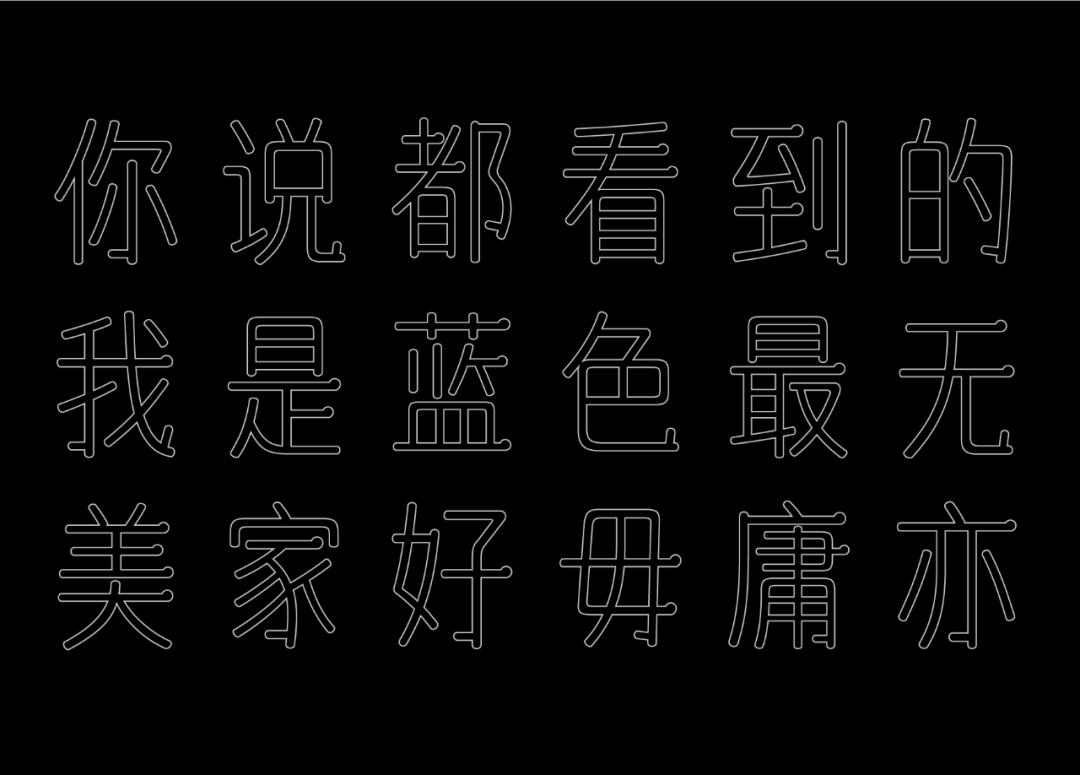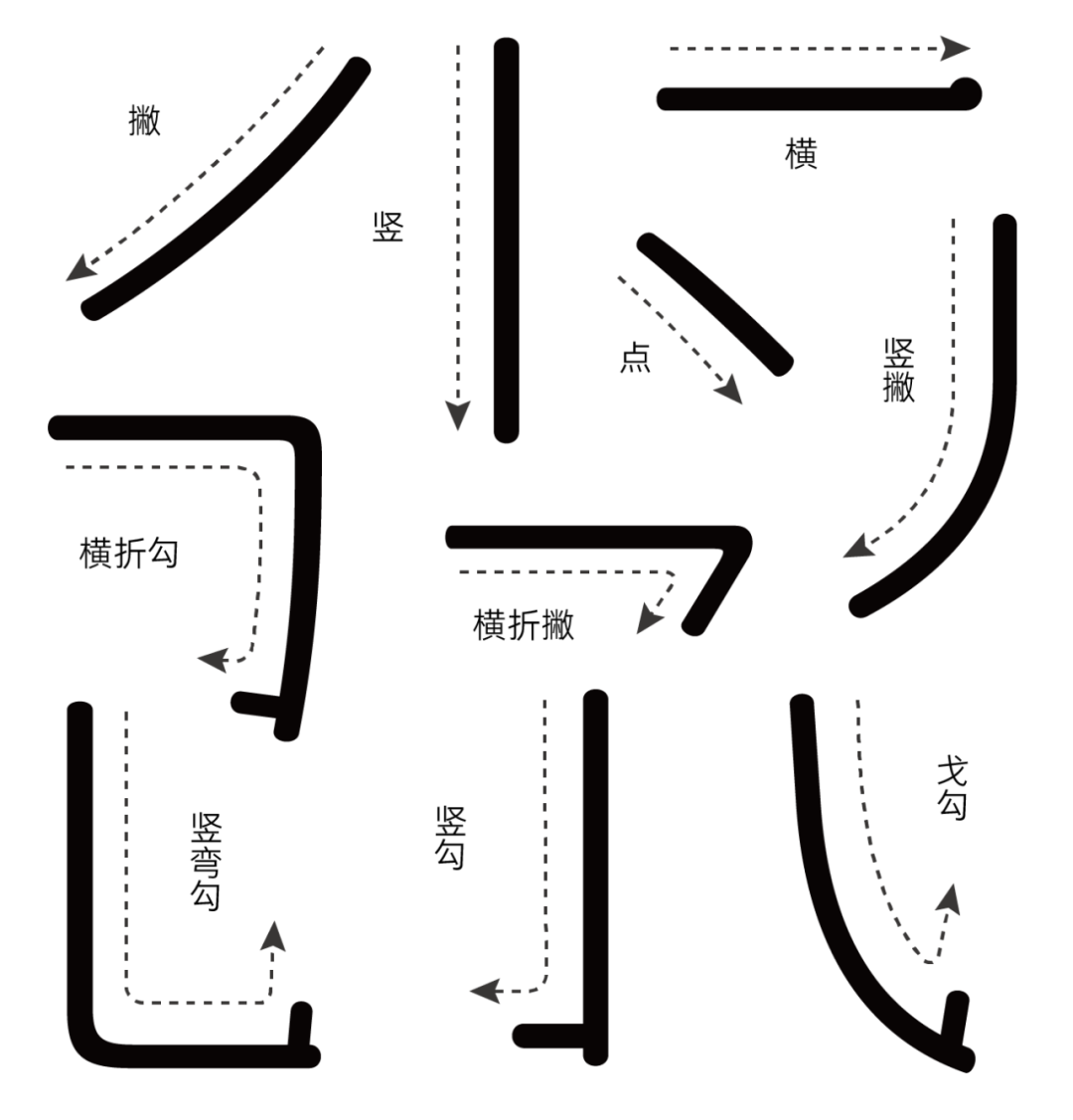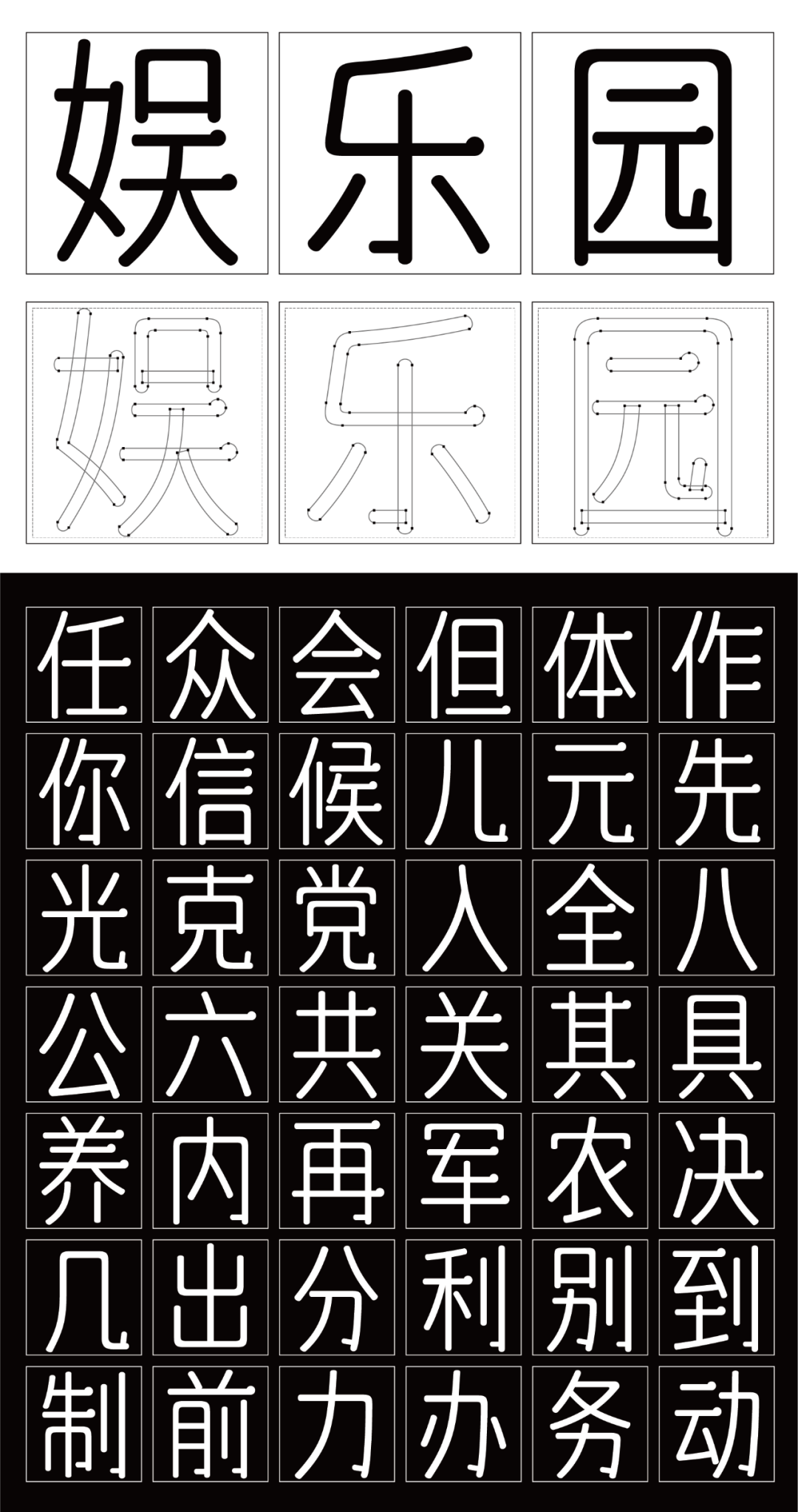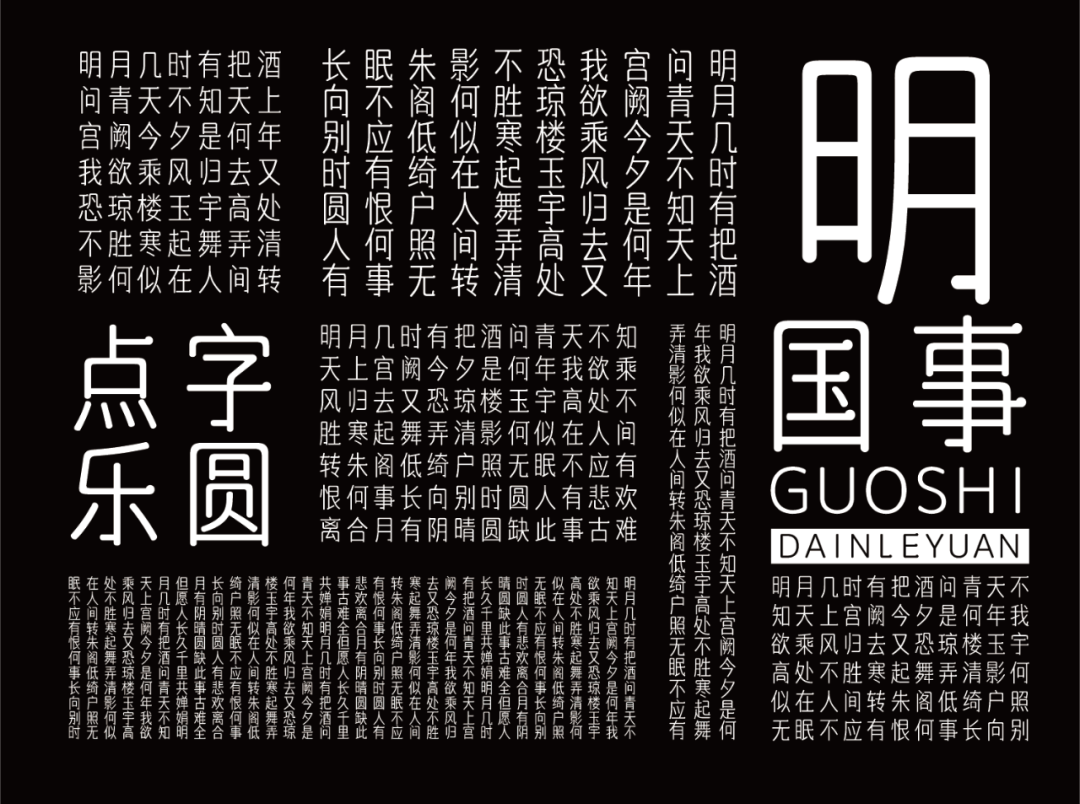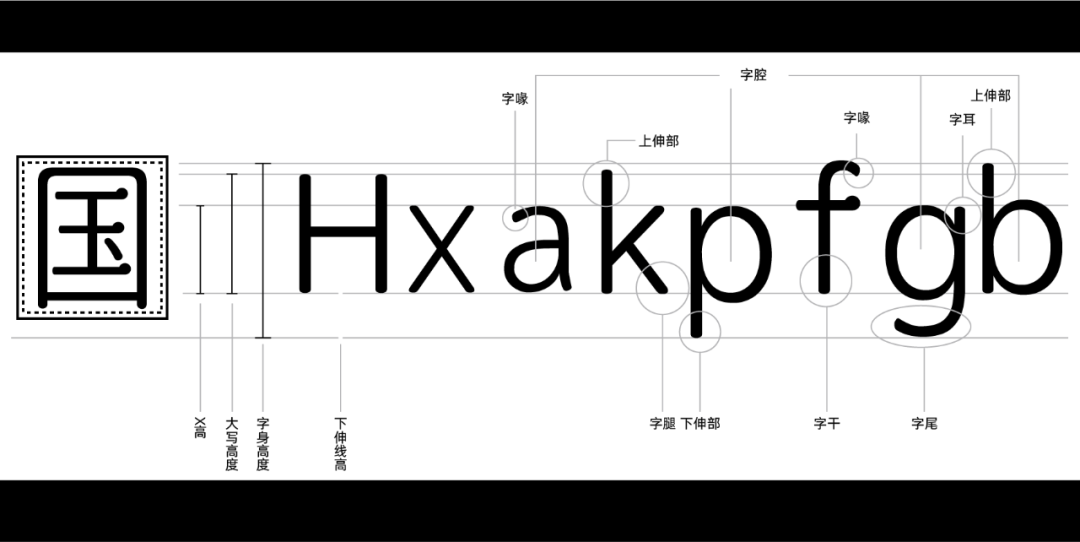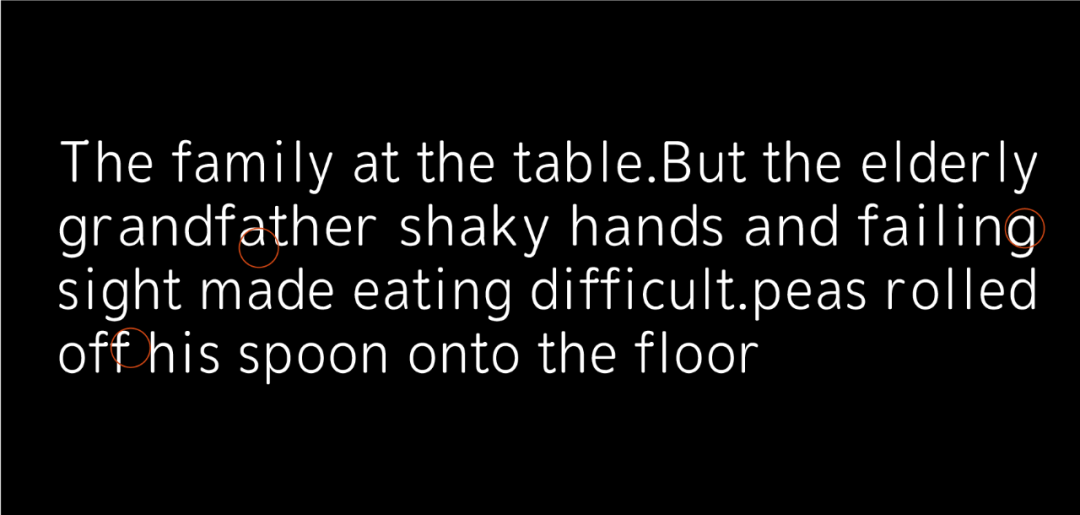
游『乐圆』带你玩转趣味圆体
追溯起圆体的历史,在中国大概出现于清末时期。biu哥这里推测圆体的出现很大程度上是受到到日本圆体即「丸ゴシック体」的影响。最早的丸ゴシック体的特征出现在1900年左右的製文堂的活字,并在秀英舎1914年出版的『活版見本帳』中有记载。而现代的成体系化的丸ゴシック体的设计起源,可以认为是写研公司1956年发表的「石井中丸ゴシック体」。
随着时代文化潮流的发展,圆体那圆润的外形使其在中文语境下更多的是应用于富有亲和力及需要柔和氛围之中。这一点与我们的邻国日本就完全不同了,日本则是将圆体当做基础用字广泛使用,有点像我国使用黑体字。
这里究竟是什么原因让圆体在日本使用度如此火爆biu哥便不得而知,但感觉以后来一篇关于分析日本圆体字的文章也许会很不错!
而今天biu哥为大家推送的这款新字体便是依托于圆体字柔和的笔画特征进行设计再创作,它便是点字库最新字体。
点字乐圆体